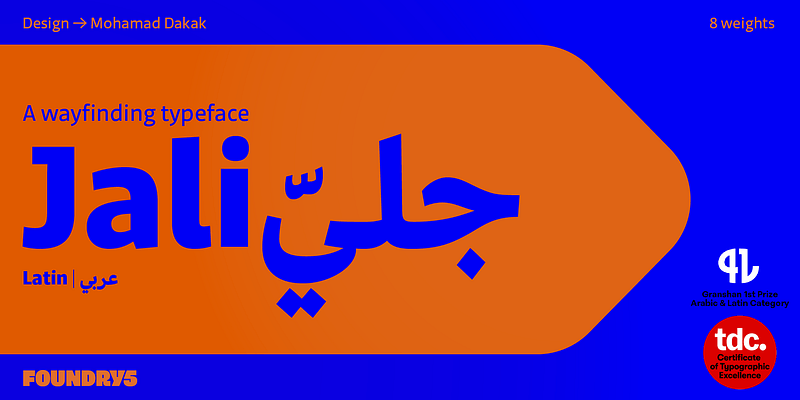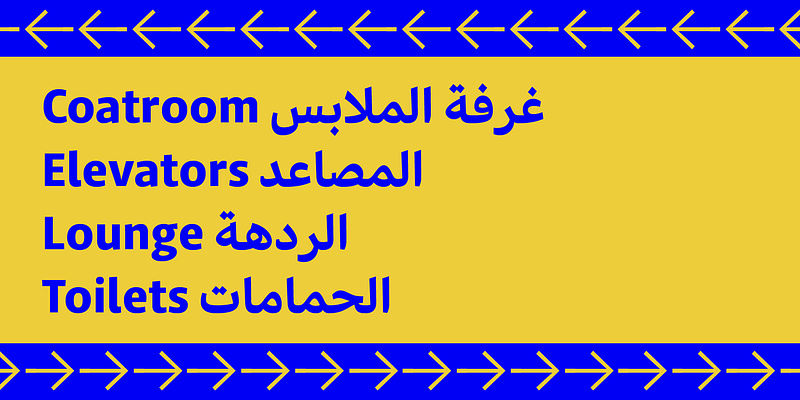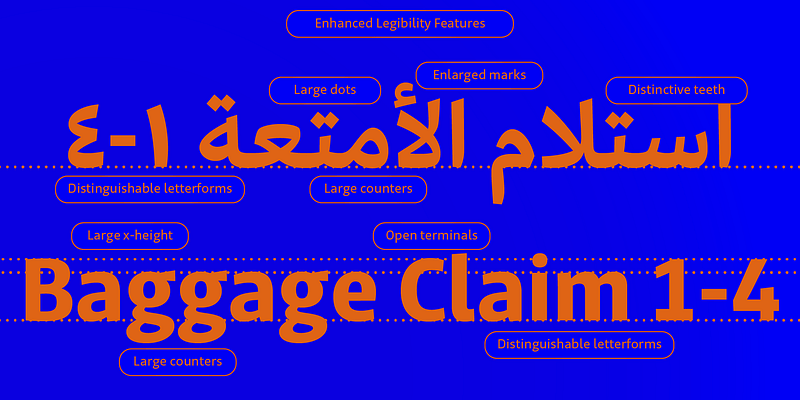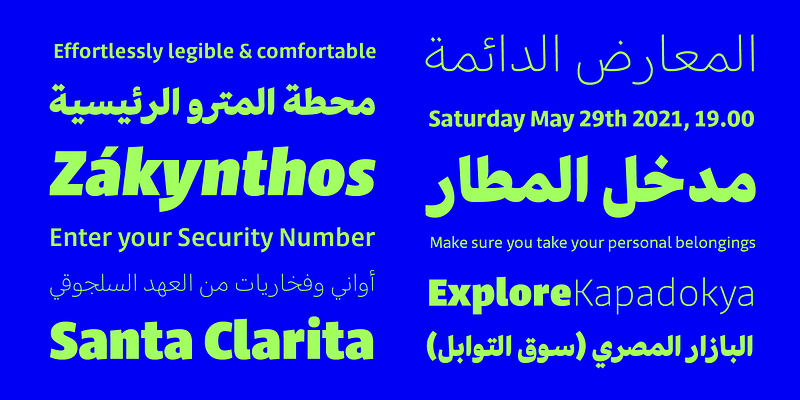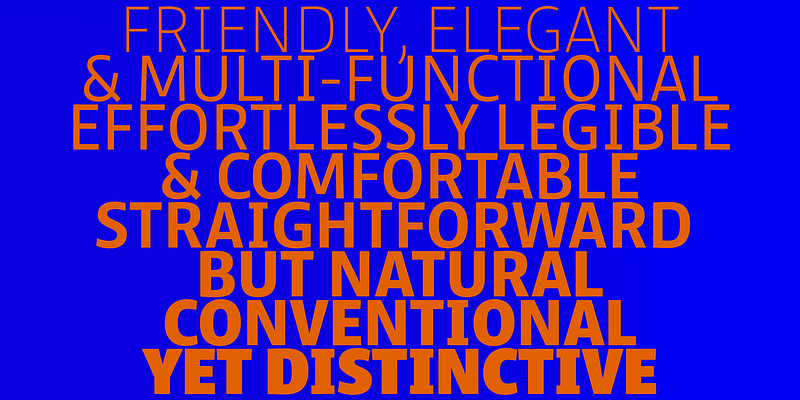
Jali はヒューマニストのサンセリフ書体で、特に案内表示に適しています。Jali はアラビア語、ギリシャ語、ラテン語を調和させながら、すべてのスクリプトに対して各言語特有のトーンを維持しています。
このデザインコンセプトの始まりは、デザインと読みやすさの要件を適切に満たすアラビア語の書体が不足していることをきっかけに行われた卒業制作でした。このプロジェクトは後に商用向けとして位置づけられ、サポートされているスクリプトでタイプファミリーの可能性を最大限に引き出すために拡張されました。
「Jali」という名前は、アラビア語で明快という意味を持っています。Jali のデザインは、その名の精神を反映しています。コントラストの低いストローク、豊富なスペースを持つカウンター、ドット、識別可能なマークの組み合わせにより、Jali は汎用性の高い書体となっています。ヒューマニスト調のトーンと明快な文字により、Jali は暖かく効率的な読書体験の提供を目指しています。案内表示に適した他の書体ファミリーと同様に、Jali は要求の厳しいタイポグラフィ環境にも適しています。